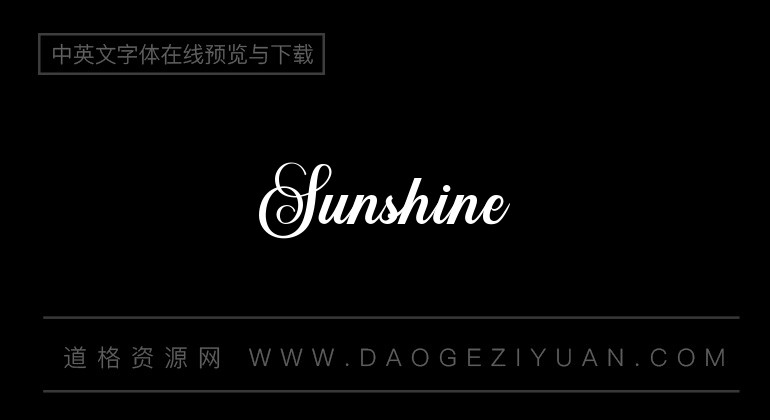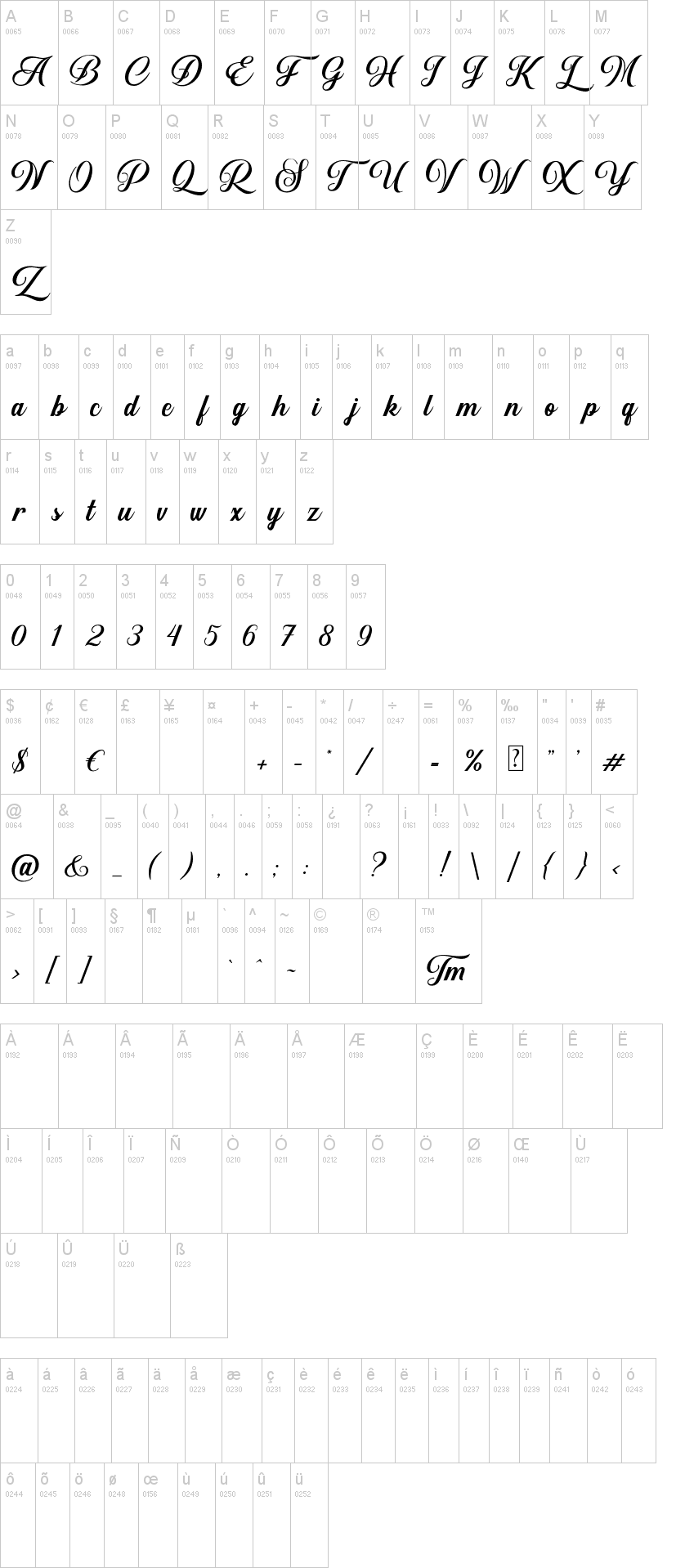
Sunshine 字体是一种简洁、可读性强的英文字体,它的字体风格结合了西方和东方的元素,形成了一种独特的多元文化融合字体。它拥有细腻的笔画,清晰的结构,使得它能够很好地传达出文字的信息,同时也能够给读者带来舒适的视觉体验。Sunshine 字体适用于各种类型的文字,包括新闻文章、博客文章、书籍、网页、广告等,是一种非常适合用于桌面出版和网络出版的字体。内容介绍
Sunshine是一款非常不错的手写艺术字体,具有很好的视觉感,适合于文化类的宣传设计、商业类品牌的广告和产品包装设计以及个性化文字排版等较多场景。